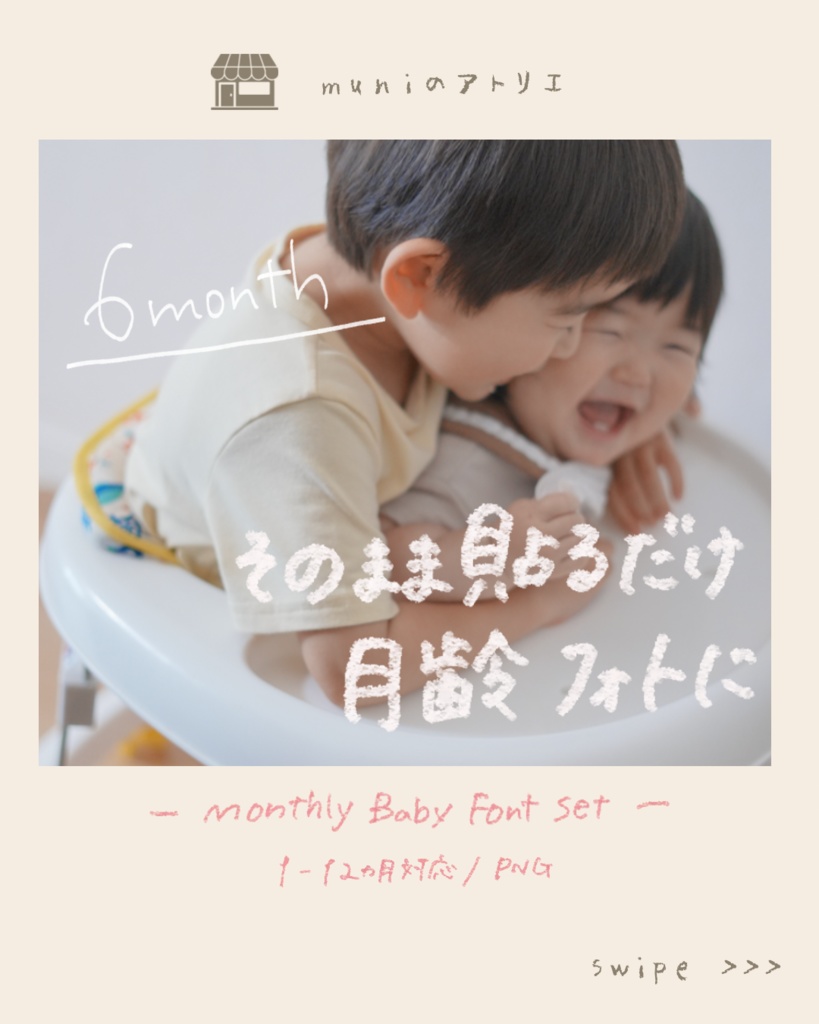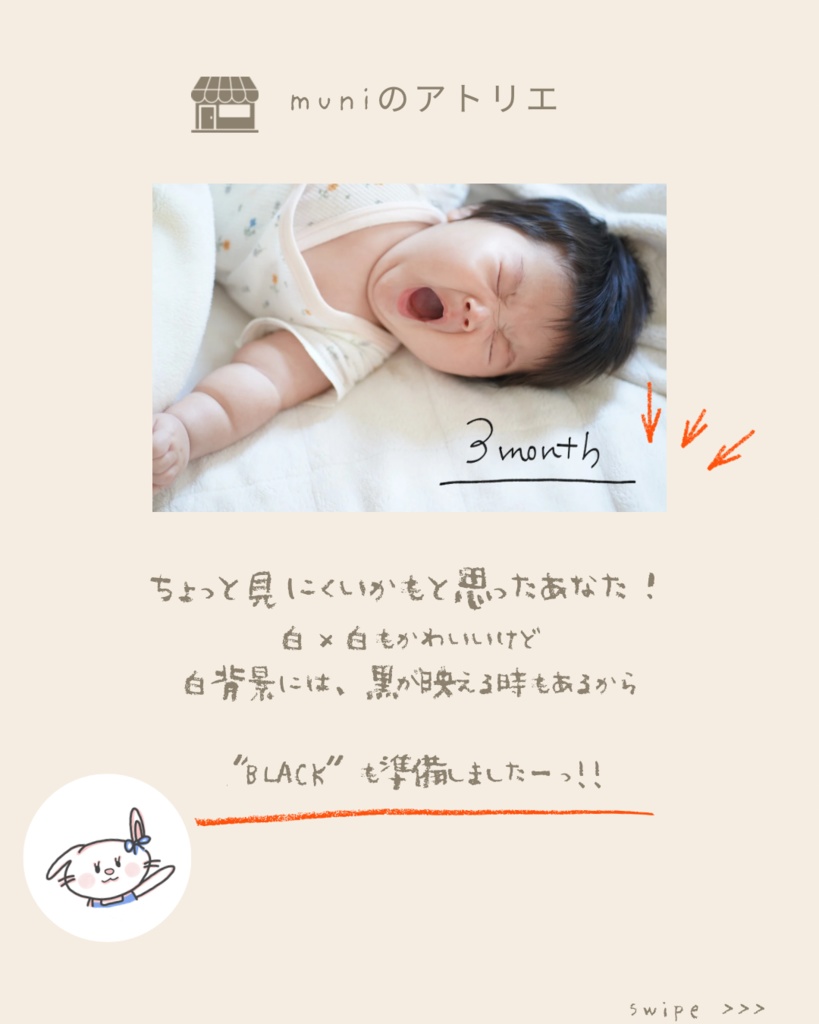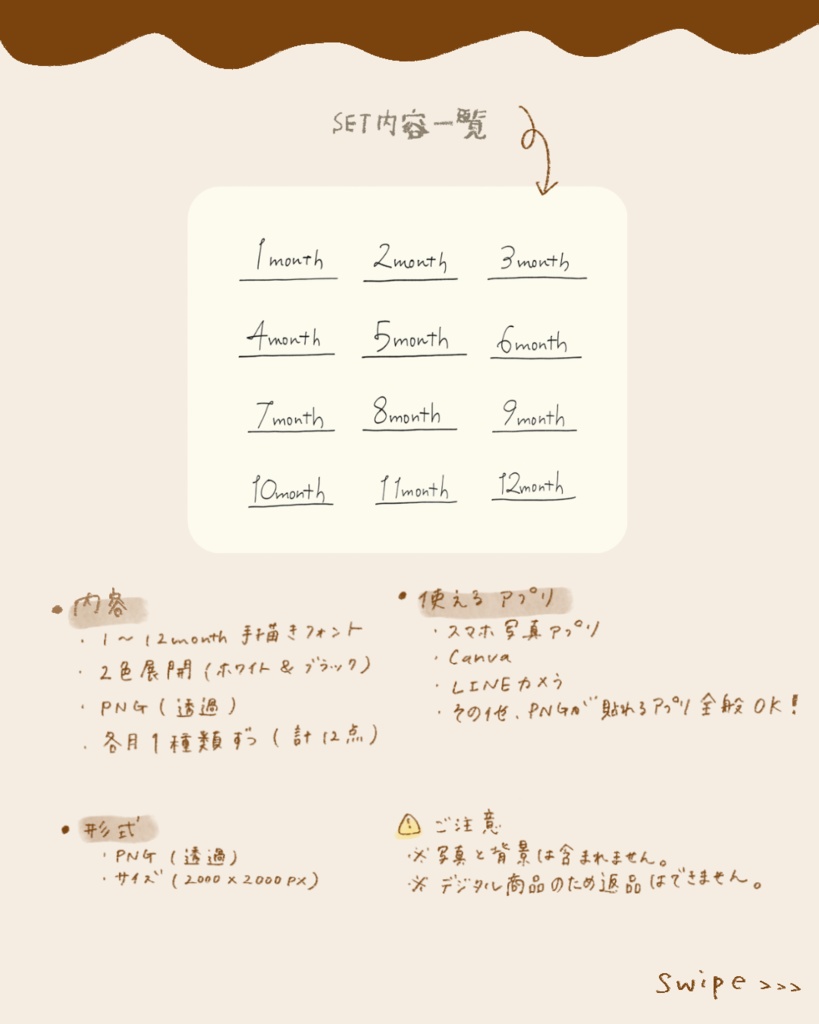
手描き月齢フォント(1〜12month/white&black/PNG)|Monthly Baby Font Set
ようこそ muniのアトリエ へ 🐰🎀 リボンうさぎの店長“むに”がつくった、 やさしい手描きの月齢フォントセットです。 Welcome to muni’s Atelier 🐰🎀 This is a soft, hand-drawn monthly font set to make your baby’s photos even more precious.
1〜12month の手描きフォント(計12種) • 2色展開:white / black • いずれも PNG(透過) 形式 • 写真にそのまま貼るだけで使えます ※ 1ヶ月ごとに 1種類ずつ(白&黒) の収録です ※ 全24点(12ヶ月 × 2色) • 1–12 month text (12 designs) • White & Black versions • PNG / transparent • Easy to use on any photo app